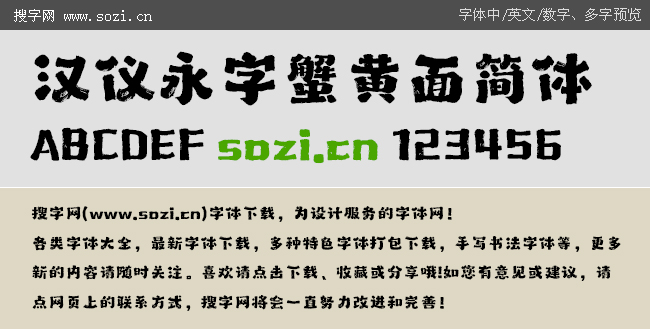
漢儀永字蟹黃面簡(jiǎn)體
搜字網(wǎng)給大家提供一款漢儀永字蟹黃面簡(jiǎn)體中文字體下載,漢儀永字蟹黃面簡(jiǎn)體是一款手寫(xiě)風(fēng)格的書(shū)法字體,字體效果非常不錯(cuò),非常有趣味性。適用于畫(huà)冊(cè)設(shè)計(jì)、海報(bào)設(shè)計(jì)、包裝設(shè)計(jì)等場(chǎng)合使用。(本字體為個(gè)人非商用版,如需要商用請(qǐng)聯(lián)系漢儀公司購(gòu)買版權(quán))
- 風(fēng)格類別: 手寫(xiě)書(shū)法體